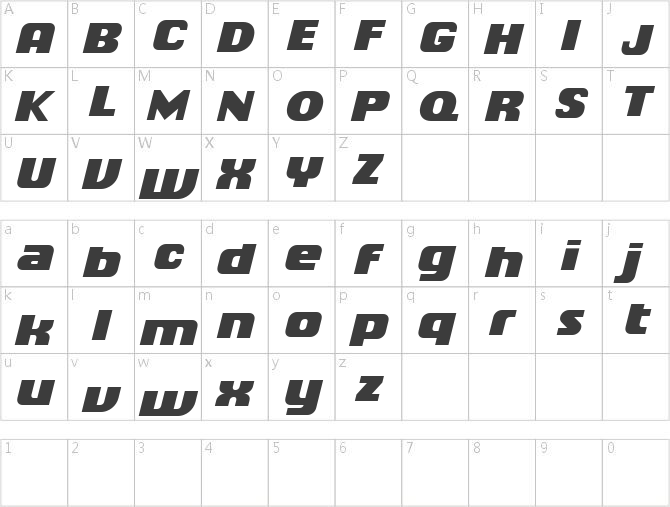
Chiq_Reduced_BlackItalic
Chiq_Reduced_BlackItalic字體字庫是一款讓人賞心悅目、百看不厭的英文字體,適合各類廣告和產(chǎn)品包裝設(shè)計應(yīng)用,字體大小0.01MB,格式為ttf字體,上傳用戶是sygyve520,作者/版權(quán)方為未知